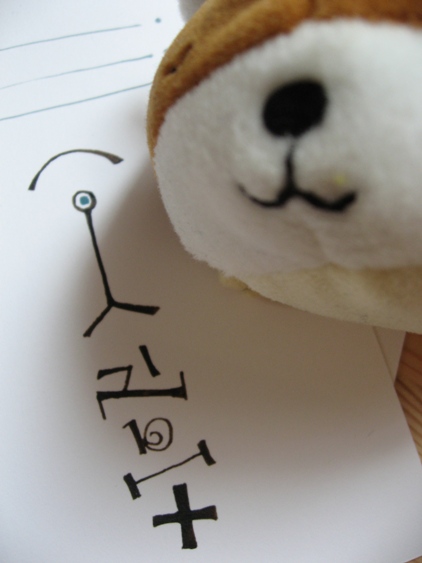
ポッチンの似顔…鼻?
「ご主人さま…!ご主人さま〜、〜、〜!」
なんですか?ポッチン…ブーキュー(鹿児島の友)ちゃんが
どうかしたの?
「ち、ち、違います。
こちらに…わたくしの似顔…鼻…似顔絵でございましようか…?」
まぁ〜、よかったわね〜!ポッチンにそっくりよ!
これはね!熊本のY嬢から頂いたカードですよ!手書きですよ!
何てすてきなんでしょう〜。
あらぁ〜、でも…ポッチンの似顔絵とは聞いていませんでしたよ。
「…さようでございますか…。しかしながら…わたくしによう似ております…。
ポッ!大変うれしゅうございます。キュ〜ン…
」
ポッチン!みんなあなたのこと可愛がってくれてますよ!みなさんの優しい心に
感謝しましょうね…。
・・・・・・・・・・・・・・・・・・・って!ポッチン、それ逆さ?
「はっ?さ・か・さ・?…とは?」
これは、Tahnk youカードなんですよ、ポッチン!
ほら、本当はこっちが上!
あらぁ〜、でもどっちからでも、ポッチンの顔入りに
見えてしまうわ…!
Y嬢さま、予期せぬ出来事となりました。
このカードはポッチンと私の宝物として大事にさせて
頂きますねぇ〜!
熊本の香りをのせてやってきたカードでした!
ポッチンさまへの想いが知らず知らずのうちにでてきてしまったようでございます。
きっとわたしの頭のなかにポッチンさまがいらっしゃるのですねぇ。
だってポッチンさまって……キュートすぎます…(はーと)。
ポッチンは、今、鹿児島ブーキューちゃんと、
熊本Y嬢さまのthank youカードとの三位一体で
幸せそうに暮らしております!
sayakaさんの文字は宇宙してますよね…。
天空に浮かんでいる星座のようにも見えます。